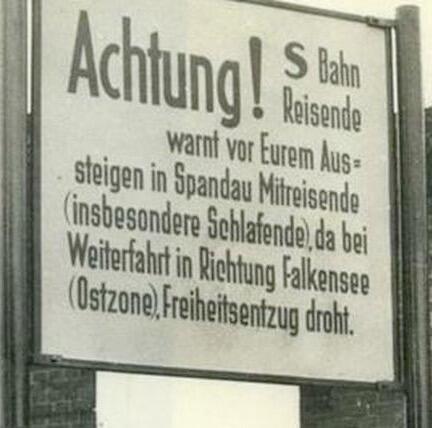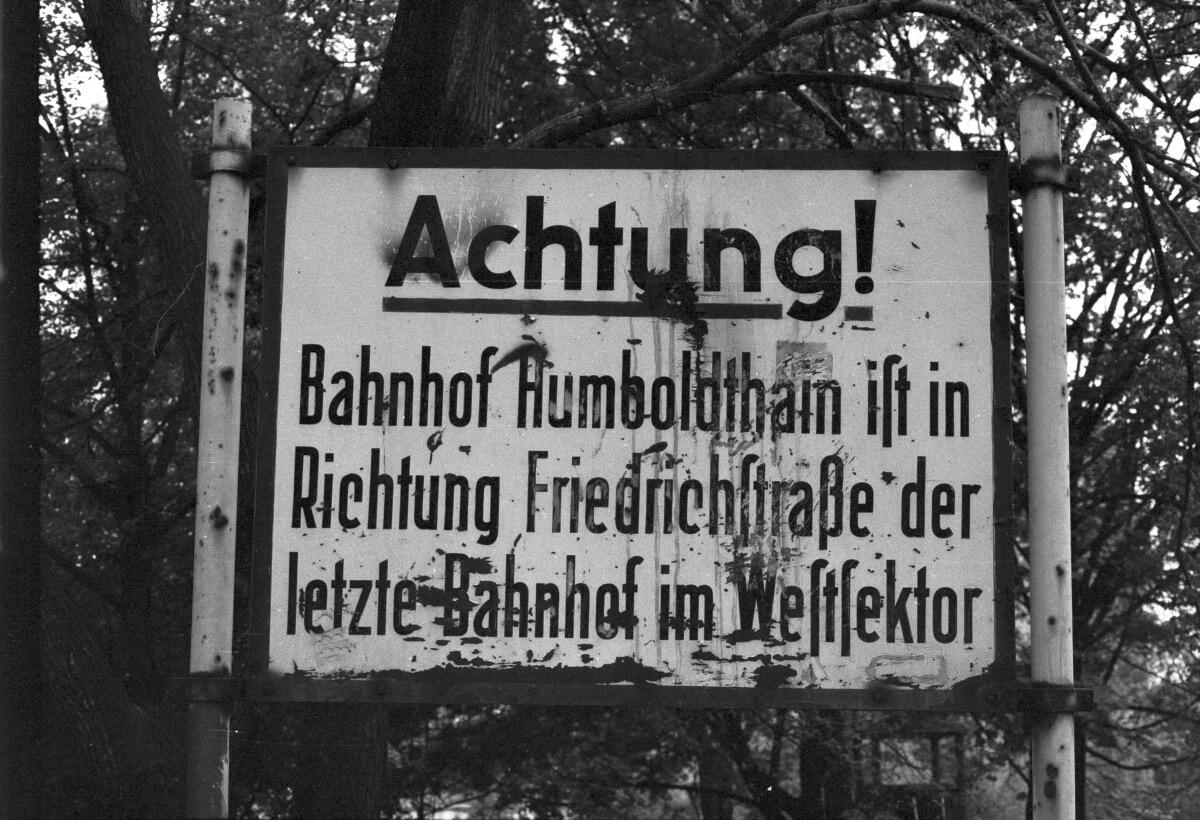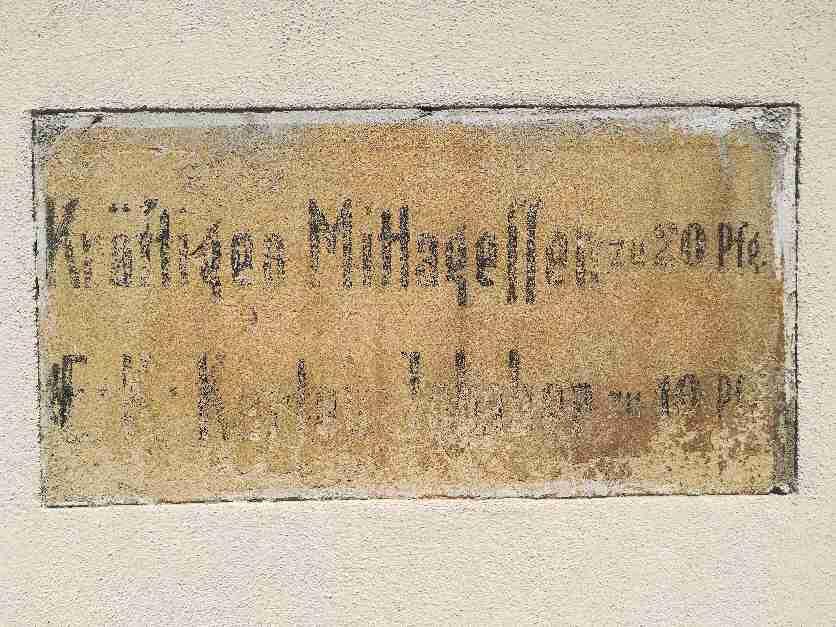
Wie heißt diese Schilderschrift?
Auf diese Schilderschrift traf man häufig in den 50er und 60er Jahren, sie schien eine Art DIN-Schrift in jenen Zeiten gewesen zu sein. Sehr auffällig sind das kleine „e“ und „c“ mit ihren „Wasserköpfen“.
Sowas kam aus Schildermalerwerkstätten. Die Zeichen waren handgemalt oder man erstellte sich Schablonen, die man aber nicht benennen musste, da sie nicht wie Druckschriften im Handel vertrieben wurden.
Ein digitaler Font in diesem Stil: http://www.peter-wiegel.de/BerlinerWand.html
Auch ein Blick wert: http://www.peter-wiegel.de/KKBahn.html
So recht mag ich gar nicht glauben, dass diese doch sehr konsequent ausgeführte Schriftart keinen eigenen Namen hatte, denn sie war – ohne große visuelle Abweichungen – auffällig oft an vielen Orten zu sehen. Ihr besonderes Merkmal war ja die extrem schlanke Ausführung, die dazu geeignet war, lange Texte auf wenig Fläche unterzubringen.
Andere markante Schrifttypen aus dieser Zeit hatten auch eine ähnliche Erscheinungshäufigkeit und waren auf bekannte Grafiker oder Schriftgießereien zurückzuführen.
Selbst wenn diese Schriftart ausschließlich für Schilder, Bunkerwände oder Hausfassaden verwendet wurde und lediglich auf Schablonen beruhen könnte (und wahrscheinlich nie im Bleisatz „ankam“), so trat sie vor allem in sehr unterschiedlichen Schriftgrößen auf (beispielsweise bei Fassaden-Reklame) und blieb dennoch immer eindeutig wiedererkennbar.
Wir wurde denn damals kommuniziert, dass genau diese Typo vom Auftraggeber gewünscht wurde? Oder hatte man das der Einfachheit gänzlich dem fachkundigen Schilder- bzw. Wandmaler überlassen?
Ja, stimmt. Allerdings ist die Avory eine sehr moderne Typo, die sich womöglich von der klassischen Werbeschrift hat inspirieren lassen. Ansonsten hat sie nämlich kaum Ähnlichkeit mit dem Schilderklassiker 🤔🤗